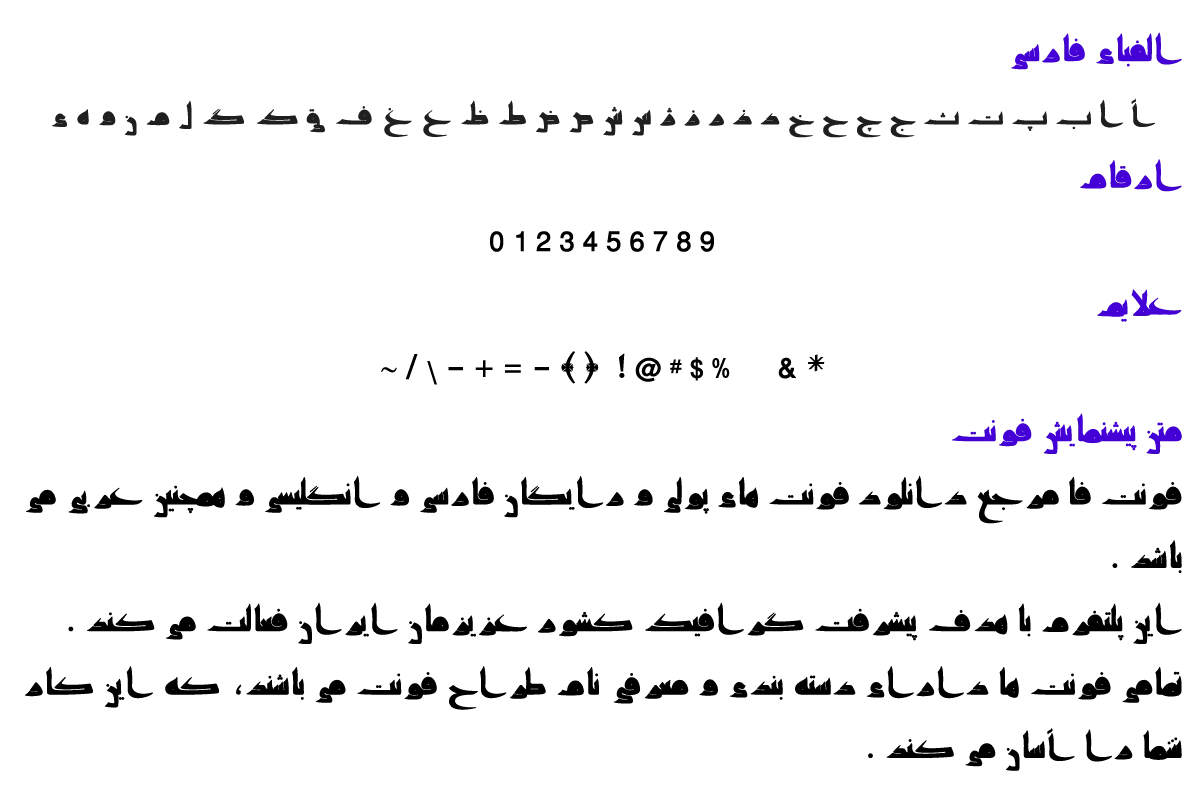
فونت فارسی مولا – Mola
توضیحات و معرفی فونت مولا
فونت فارسی مولا ( Mola ) از مجموعه فونت های آزاد می باشد، و نیز نوع فونت گرافیکی می باشد.
فونت خوشگل مربوط توسط حسین زاهدی در سال 1390 طراحی و ساخته شده است.
این تایپ فیس از براساس خط کوفی که از روی قرآن منسوب به حضرت علی (ع) ساخته شده و دارای نقطه و حروف ترکیبی و اعراب کامل می باشد.
و نیز فونت مولا در یک وزن معمولی است.